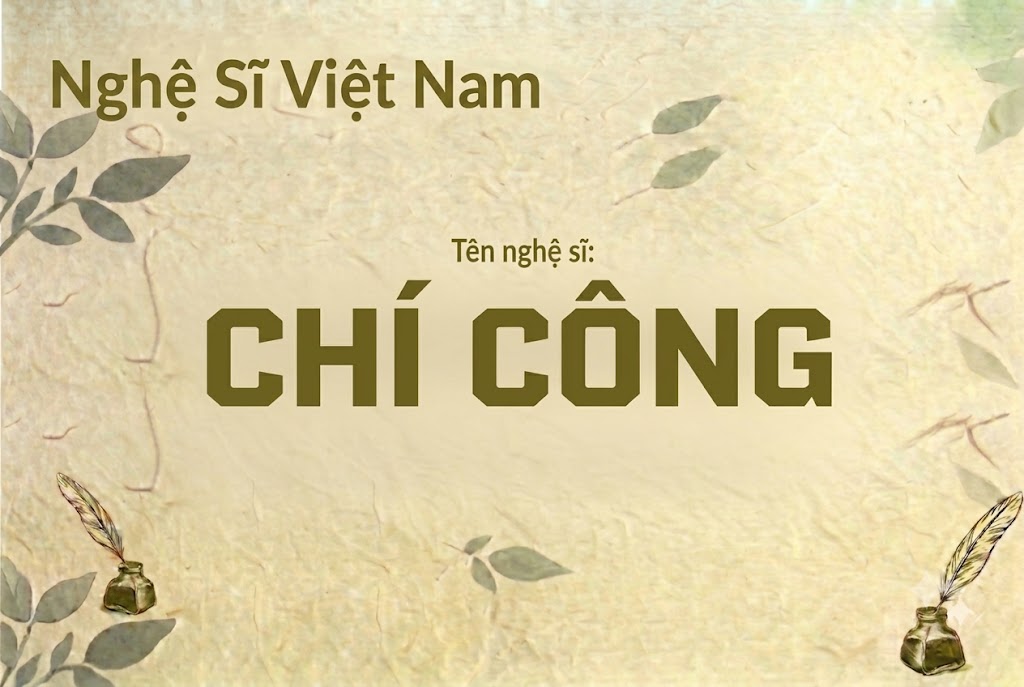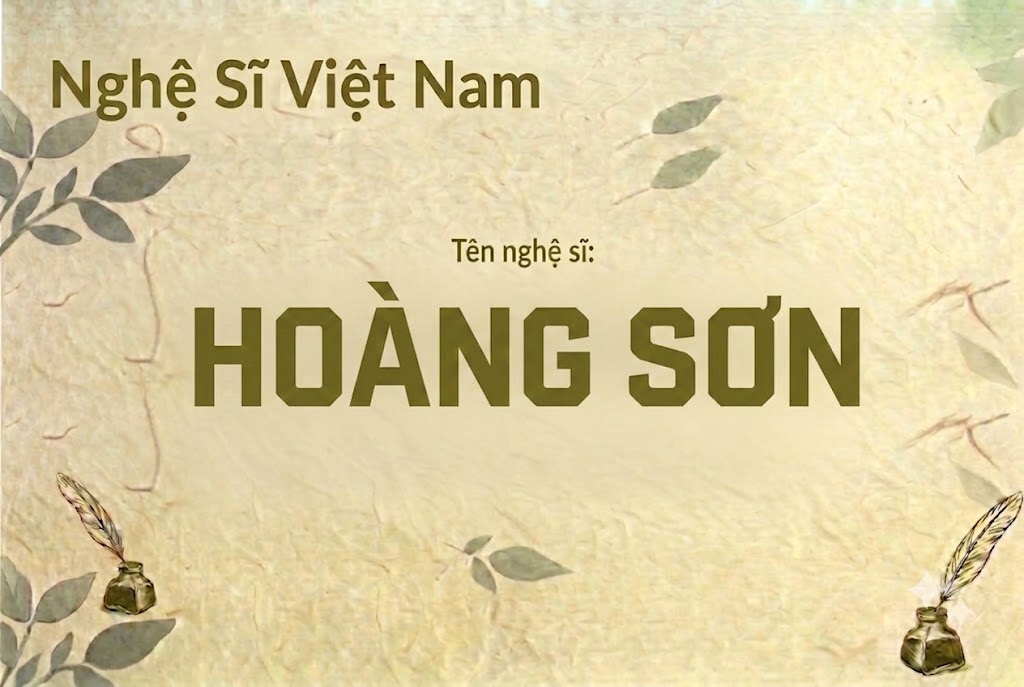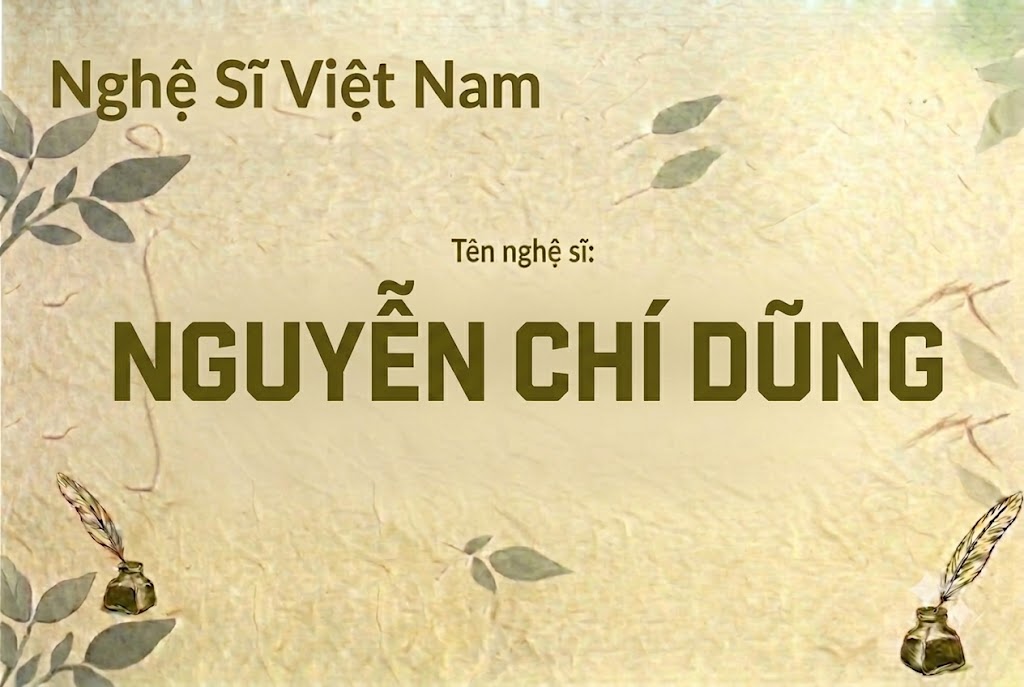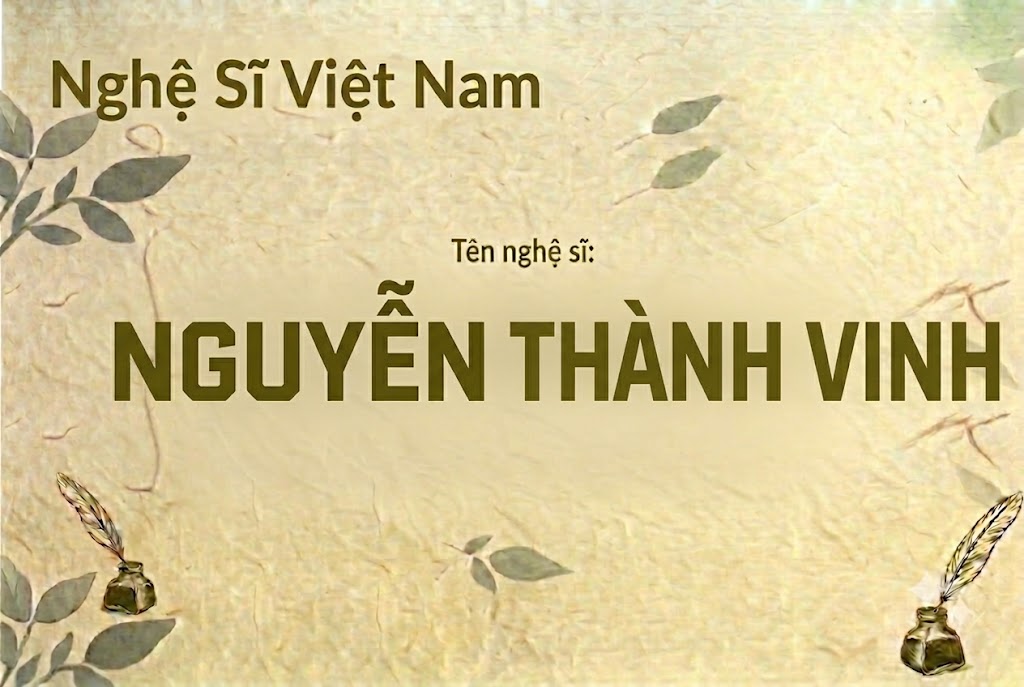
1FTV Avilock Bold
Trong việc thiết kế đồ họa truyền thông hay làm nội dung video ngắn, những phông chữ thuộc nhóm condensed (dáng cao, hẹp) luôn mang lại sự gọn gàng và tối ưu không gian hiển thị một cách xuất sắc.
Tuy nhiên, việc tìm kiếm một kiểu chữ vừa có nét dày dặn, cứng cáp lại vừa giữ được sự thanh thoát, dễ nhìn không phải là điều dễ dàng đối với các designer.
Nếu bạn đang cần một giải pháp thiết kế hoàn hảo để làm nổi bật các dòng giật tít trên thumbnail hoặc các đoạn subtitle chạy chữ, thì font 1FTV Avilock Bold chính là sự lựa chọn lý tưởng.
Giới thiệu về font 1FTV Avilock Bold
Font 1FTV Avilock Bold là một phông chữ hiển thị không chân được thiết kế với cấu trúc phom dáng cao, hẹp, mang lại cảm giác vô cùng vững chãi và gọn gàng.
Bộ font này được tối ưu hóa hoàn chỉnh ở phiên bản 1.000, đem đến sự nhất quán và đồng bộ tuyệt đối trong kết cấu cấu trúc của từng con chữ khi sắp xếp cạnh nhau.
Sản phẩm xuất hiện trong bài viết sở hữu định dạng opentype layout cao cấp, đi kèm chứng thực kỹ thuật số và hệ thống đường nét dạng postscript outlines siêu chuẩn.
Nhờ các thông số kĩ thuật tối ưu này, phông chữ có khả năng hiển thị vô cùng sắc nét, giúp bạn tự tin ứng dụng trên mọi phần mềm đồ họa hiện đại mà không sợ lỗi vỡ hình.
Được thực hiện và chia sẻ rộng rãi bởi đội ngũ 1FTV, đây là giải pháp thiết kế tuyệt vời để tạo nên sự bứt phá về mặt thị giác cho các dự án truyền thông số tại Việt Nam.
Đặc điểm nổi bật của phong cách thiết kế Avilock Bold
Sức hút lớn nhất của font 1FTV Avilock Bold đến từ kiểu dáng condensed thuôn dài theo chiều dọc kết hợp cùng các nét chữ siêu đậm đầy mạnh mẽ.
Thiết kế đặc trưng này giúp bạn có thể dễ dàng chèn được các câu tiêu đề dài vào những không gian chật hẹp mà không sợ chữ bị tràn viền hay gây cảm giác ngột ngạt.
Các góc chữ được bo viền dứt khoát và vuông vắn, tạo nên một cảm giác vô cùng hiện đại, chắc chắn, mang đậm hơi hướng công nghệ và thể thao đô thị.
Phông chữ được xây dựng theo cấu trúc all-caps (viết hoa toàn bộ), giúp tạo ra sự đồng đều tuyệt đối về mặt cao độ, khiến các khối chữ của bạn trông như một tác phẩm đồ họa kiên cố.
Để phông chữ vận hành mượt mà trên mọi hệ thống máy tính, phiên bản font 1FTV Avilock Bold đã trải qua quy trình xử lý thông số kĩ thuật vô cùng kỹ lưỡng.
Hệ thống khoảng cách chữ (kerning) và độ giãn dòng (tracking) đã được căn chỉnh chuẩn xác, giúp các từ khi đứng cạnh nhau luôn giữ được khoảng trống thẩm mỹ tốt nhất.
Bên cạnh hệ thống chữ cái viết hoa đồng bộ, phông chữ còn tích hợp đầy đủ dãy số từ 0-9 cùng hệ thống các ký tự đặc biệt, dấu câu thông dụng (1234567890.:,;'"(!?)+-*/=).
Tiện ích này giúp bạn thoải mái sáng tạo các nội dung quảng cáo hay biên tập video tiếng Việt mà không lo gặp phải tình trạng lỗi hiển thị hay bị thiếu ký tự khi gõ.
Hình ảnh demo thực tế của font 1FTV Avilock Bold
Để giúp bạn dễ dàng hình dung khả năng co giãn và hiển thị linh hoạt của phông chữ này trên các kích thước khác nhau, hãy cùng xem qua bảng mô phỏng thực tế:
Kích thước nhỏ (12pt – 24pt): Các nét chữ đậm và dáng cao condensed vẫn hiển thị rất rõ ràng, ngay ngắn, dễ đọc trên màn hình các thiết bị di động.
Kích thước lớn (36pt – 72pt): Đây là không gian lý tưởng để font chữ phô diễn toàn bộ sức mạnh hình khối, tạo hiệu ứng thị giác đè nặng mạnh mẽ cho các tiêu đề chính.
Ứng dụng của font Avilock Bold trong thiết kế đồ họa và làm video
Sở hữu nét cá tính bứt phá và phom dáng condensed linh hoạt, font 1FTV Avilock Bold mở ra không gian ứng dụng rộng lớn cho các dự án truyền thông:
Thiết kế thumbnail Youtube và ảnh thu nhỏ: Đây là vũ khí hạng nặng để tăng tỷ lệ nhấp chuột. Chữ sẽ cực kỳ nổi bật khi bạn kết hợp dáng chữ cao này với các tông màu tương phản mạnh trên nền tối.
Làm tiêu đề video ngắn (Tiktok, Shorts, Reels): Dáng chữ thuôn gọn này rất thích hợp để làm các cụm từ từ khóa chính, tiêu đề mở đầu video phong cách mạnh mẽ, giúp giữ chân người xem lướt chậm lại.
Banner và poster quảng cáo ngành giải trí, thể thao: Hoàn hảo cho các poster giải đấu thể thao điện tử (esports), banner câu lạc bộ gym, fitness, xe độ hoặc các sản phẩm sáng tạo hướng tới giới trẻ.
Nhận diện thương hiệu phong cách hiện đại: Phù hợp làm logo dạng chữ khối, biểu ngữ quảng cáo hoặc thiết kế nhãn mác cho các thương hiệu cần sự chắc chắn, trực diện và độc đáo.